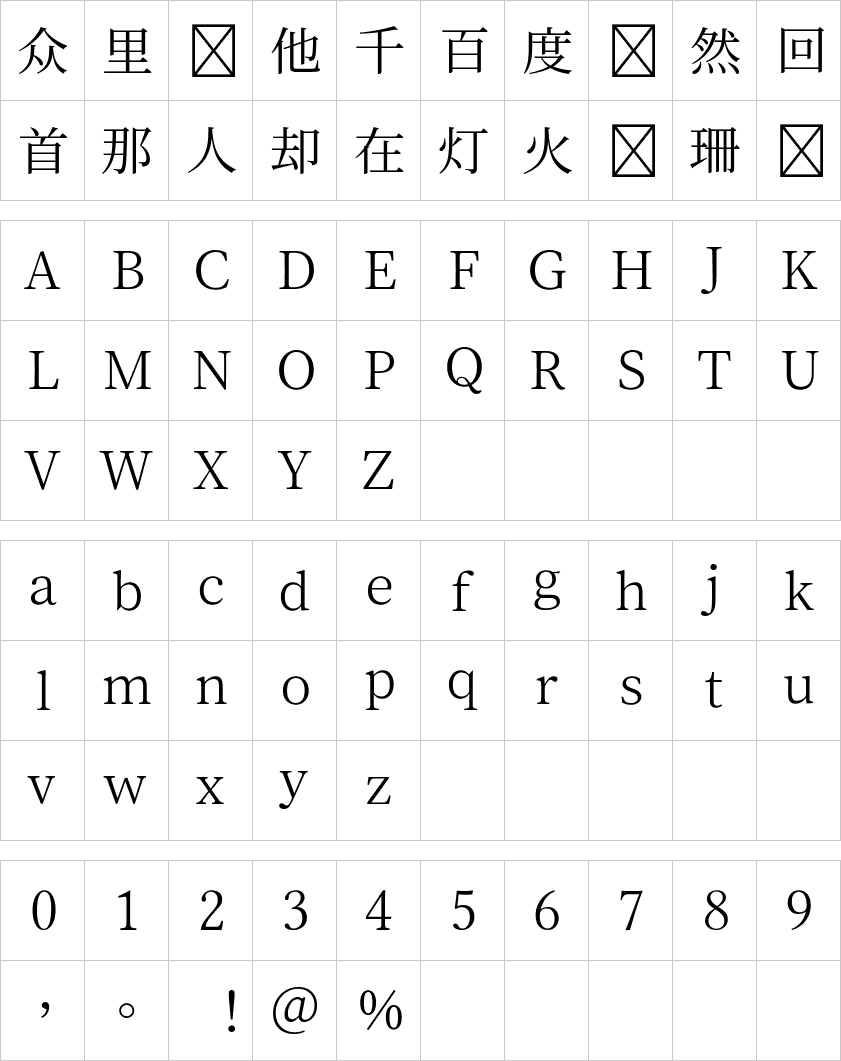
源暎こぶり明朝
“源暎こり明朝”是一种能在个人创作活动中活用的“普通”,是一种具有假名的文艺、纵组、长篇正文明朝体。
在个人进行创作活动时,不用为许可证而烦恼,可以用于“自由”的开源明朝体中,已经存在着“IPAex明朝”和“源之明朝”等。但是这些都是通用的,或者是适合在显示器上横排显示的设计,所以在竖排长句的小说正文中使用的假名很大等特征。
因此,将专门制作竖排小说的平假名与源之明朝合二为一自制的同时,作为一个综合字体调整后的是“源影明朝”。